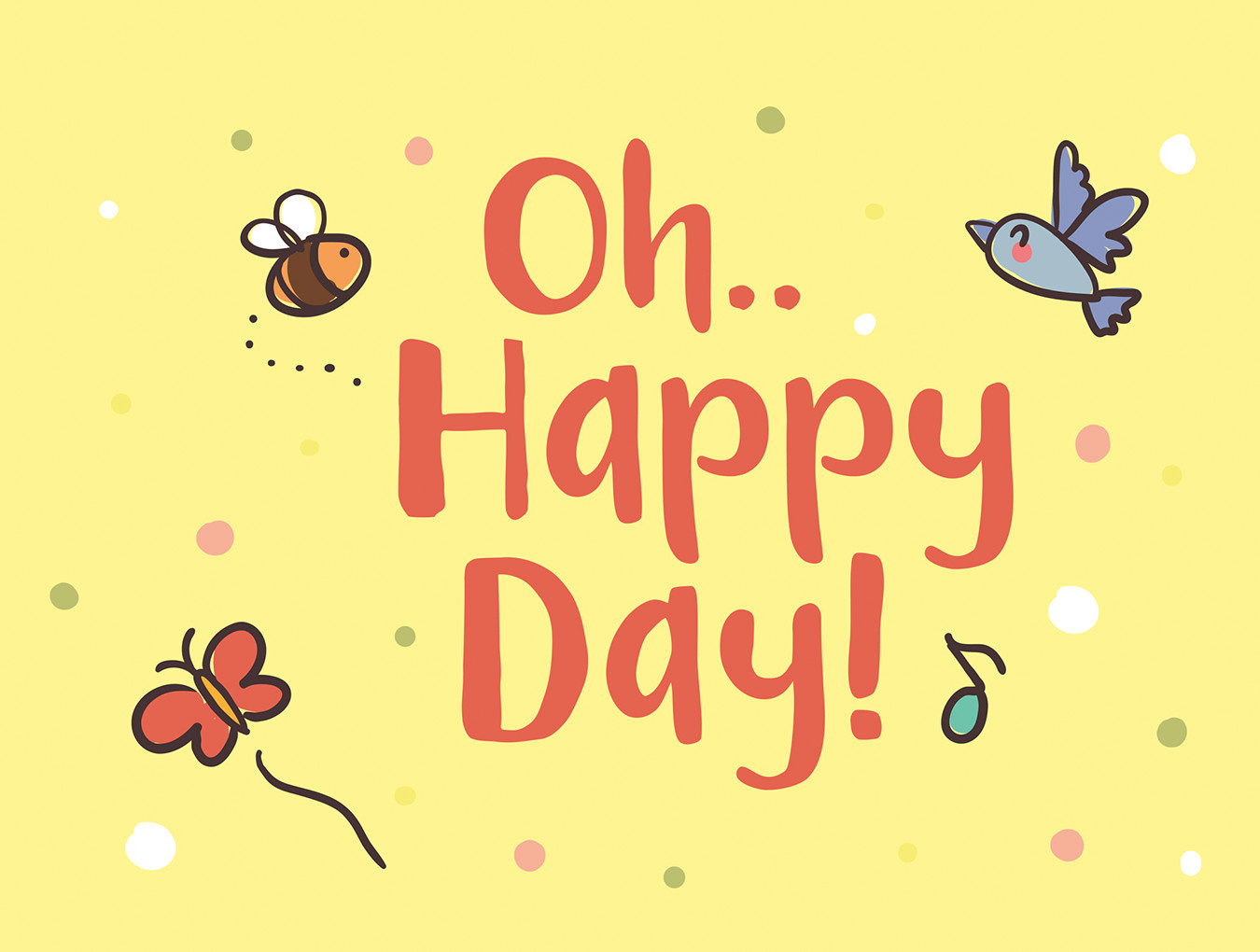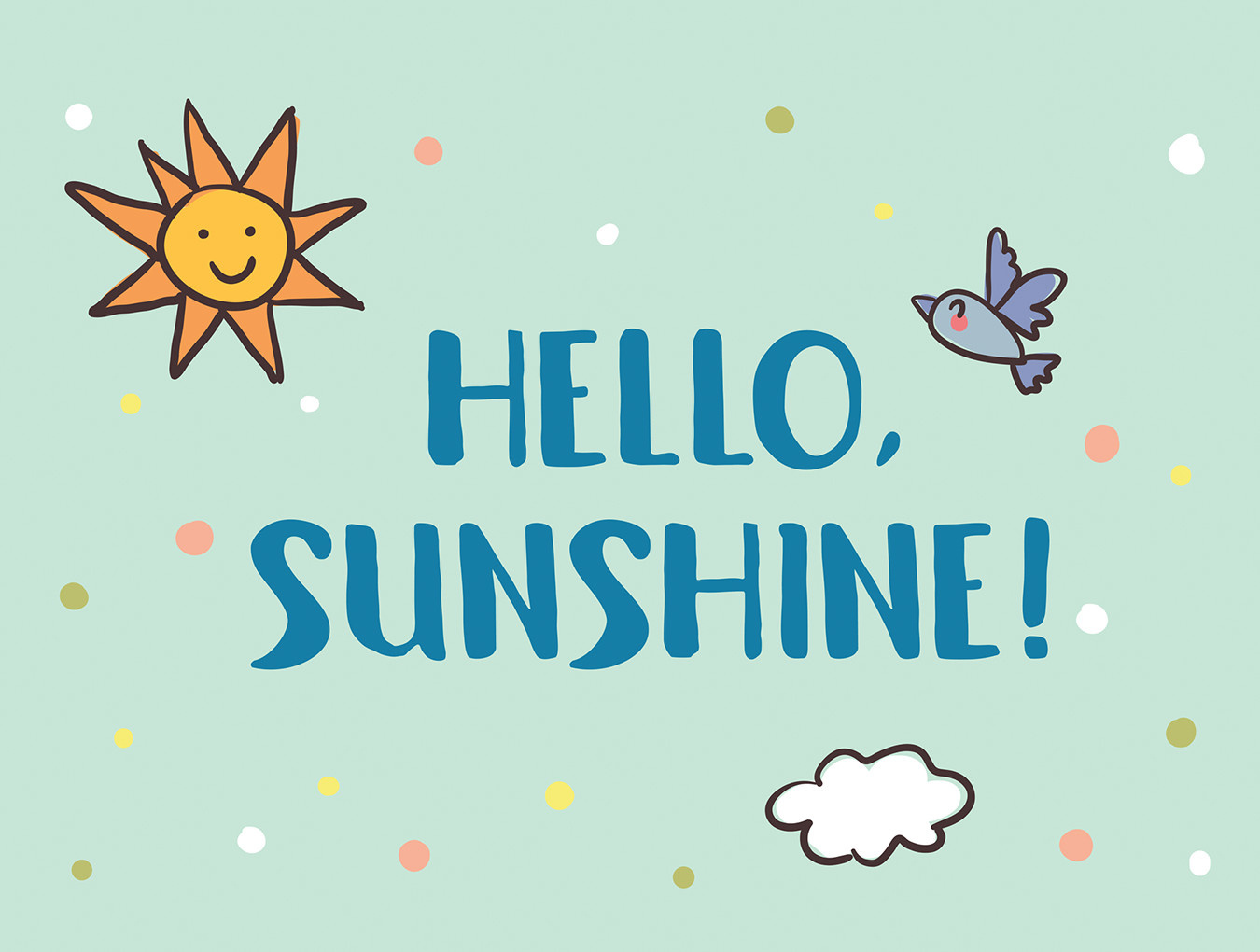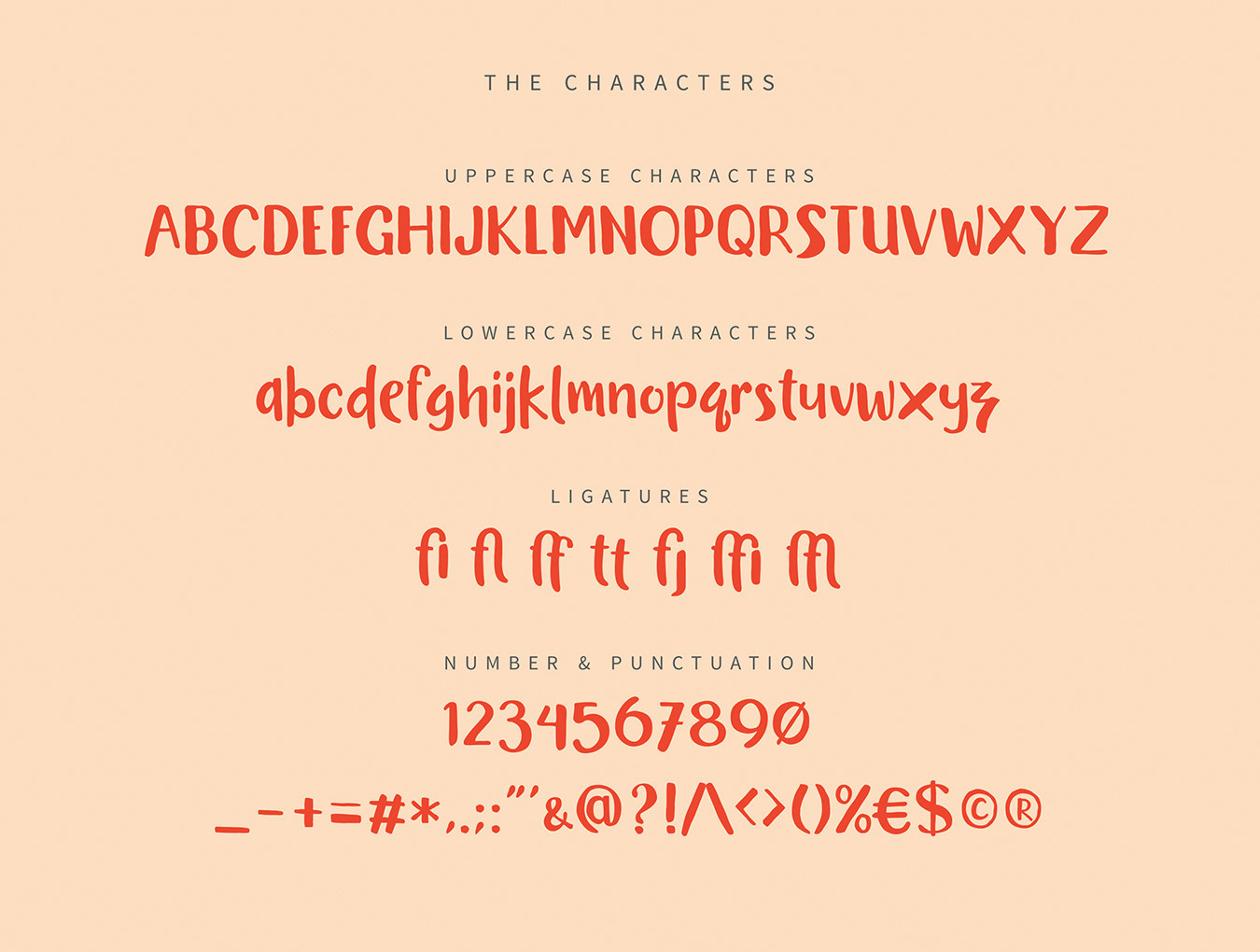
简单,有趣且易于阅读的字体,Book Worm Typeface
A simple, fun & easy to read typeface, Book Worm Typeface
介绍书虫!简单,有趣且易于阅读的字体。 基于用画笔创建手工刻字,这种字体的灵感来自儿童故事书。这种字体通过易于阅读和有趣的角色为阅读书籍增添了更多乐趣。包括简单的连字,数字和标点符号,这种字体可用于引号,标题和正文!